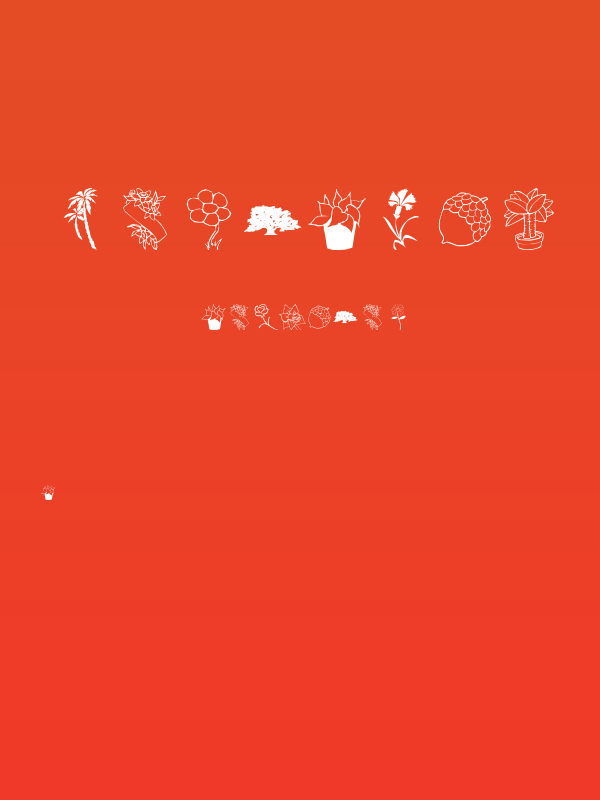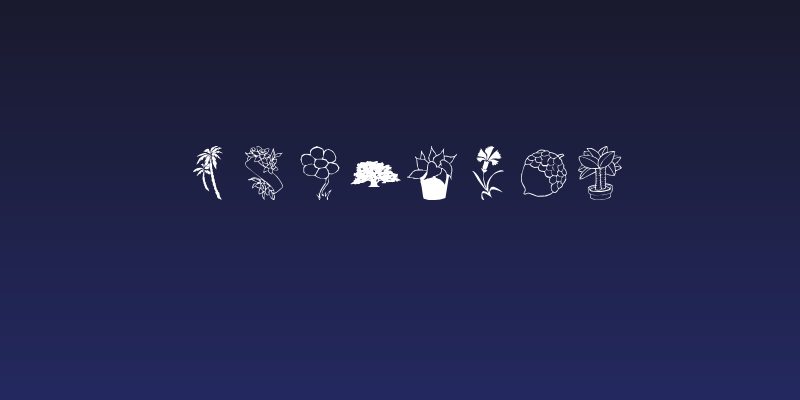
lpnature Font
| Stile generale | Decorative, Hand-drawn, Organic |
| Caso d'uso | Logos, Decorative headings, Themed illustrations, Craft projects |
| Progetti proposti | Nature-themed branding, eco-friendly packaging, greeting cards, educational materials, decorative posters. |